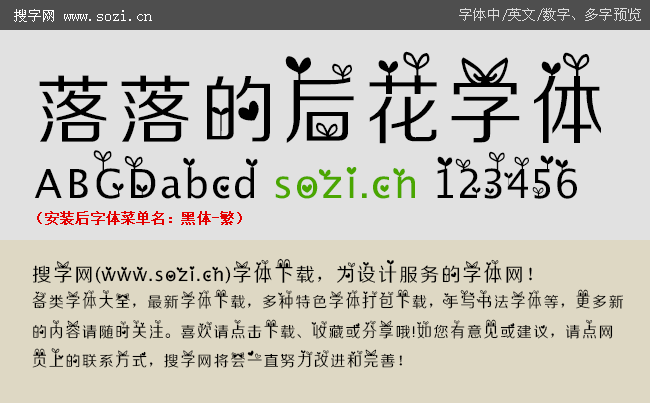
落落的后花園字體
搜字網(wǎng)給大家提供一款很可愛的手機(jī)中文字體下載。喜歡安靜而又有些文藝控的朋友有時(shí)也想讓自己的手機(jī)字體個(gè)性一些,這款手機(jī)字體就很適合了,這款手機(jī)字體是在方正正黑體上進(jìn)行修改,筆畫間插入了有趣的卡通花瓣和愛心圖案。真是又有個(gè)性,又是文藝感十足的一款字體,該中文字體圖案卡通味實(shí)足,趣味性強(qiáng),又保持了文字的識(shí)別度,適合可愛女生和擁有童心的朋友在手機(jī)上安裝使用。